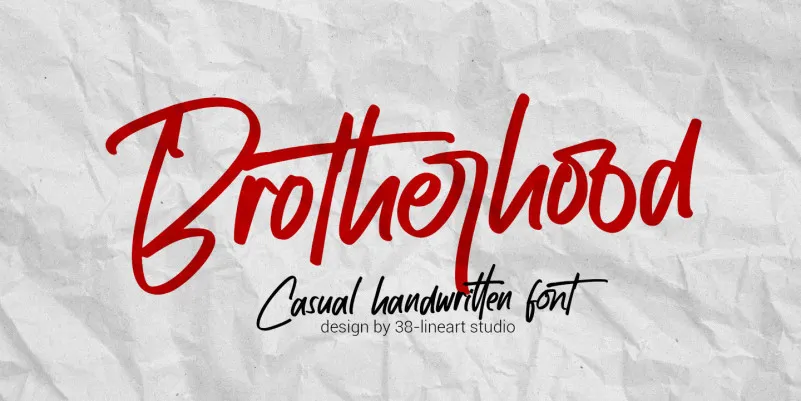
Brotherhood Font – Download Grátis
A famosa ‘Brotherhood Font’ é uma mão-dura que se encaixa perfeitamente no perfil das categorias de fontes de escreverman. Ela foi criada pelo designer 38.lineart e oferece um toque autêntico à qualquer projeto visual, seja em redes sociais, portfolios pessoais ou sites web. Com uma personalidade única que flui naturalmente, a ‘Brotherhood Font’ é perfeita para os amantes do estilo handwritten. Seja você criando um feed social atemporal com fotos da sua vida cotidiana, fazendo seu próprio portfólio profissional em uma página web ou até mesmo estilizando textos no seu site pessoal, essa fonte oferece a oportunidade de expressar o lado mais íntimo e verdadeiro do seu eu. O uso dessa fonte permite que você faça um resumo sincero da sua jornada, desde os momentos mais simples às experiências mais significativas. É ideal para quem valoriza a conectividade social e busca um modo autêntico de expressar-se na era digital. Seja qual for o seu projeto, essa fonte irá complementá-lo de forma harmoniosa.